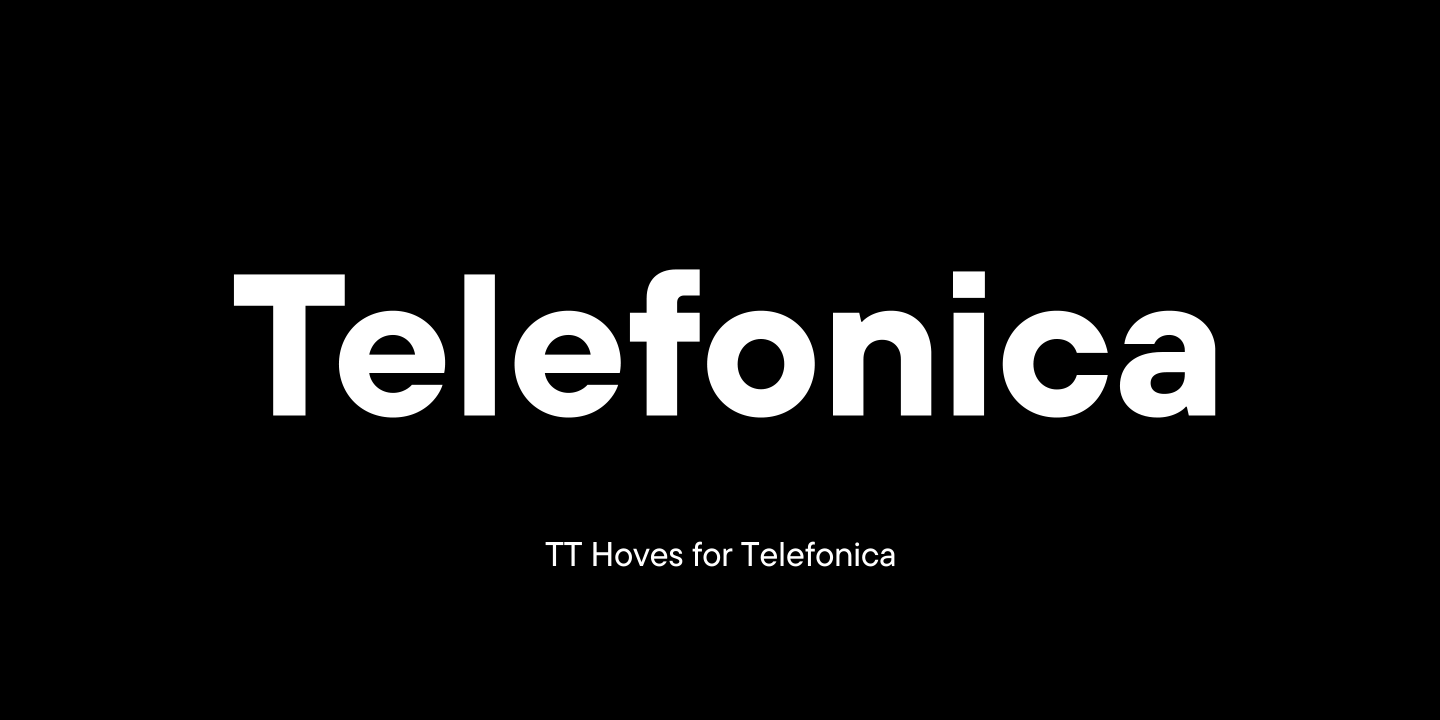
Кастомизация TT Hoves для легендарного бренда Telefonica
К команде TypeType обратилась испанская телекоммуникационная компания Telefonica с запросом на кастомизацию шрифта TT Hoves. Telefonica известна как одна из крупнейших компаний в секторе традиционной и мобильной сотовой связи в мире.
Компанию полностью устраивал шрифт, и они хотели внести только одно изменение! Однако эта кастомизация затрагивала многие символы.
Telefonica хотела изменить внешний вид всех точек и поменять их форму с квадратных на круглые, в итоге получив кастомизированную версию шрифта с новым названием. Дизайнеры TypeType приступили к работе. Были отобраны все символы и буквы, подходящие под кастомизацию, после чего в каждый глиф была внесена круглая точка.
Изменение формы точек с квадратных на круглые
Для кастомизированных знаков был сделан хинтинг, после чего шрифтовой файл получил название Telefonica Sans.
Кастомная версия TT Hoves под названием Telefonica Sans стала более дружелюбной для восприятия. Результат вы можете увидеть на сайте компании.